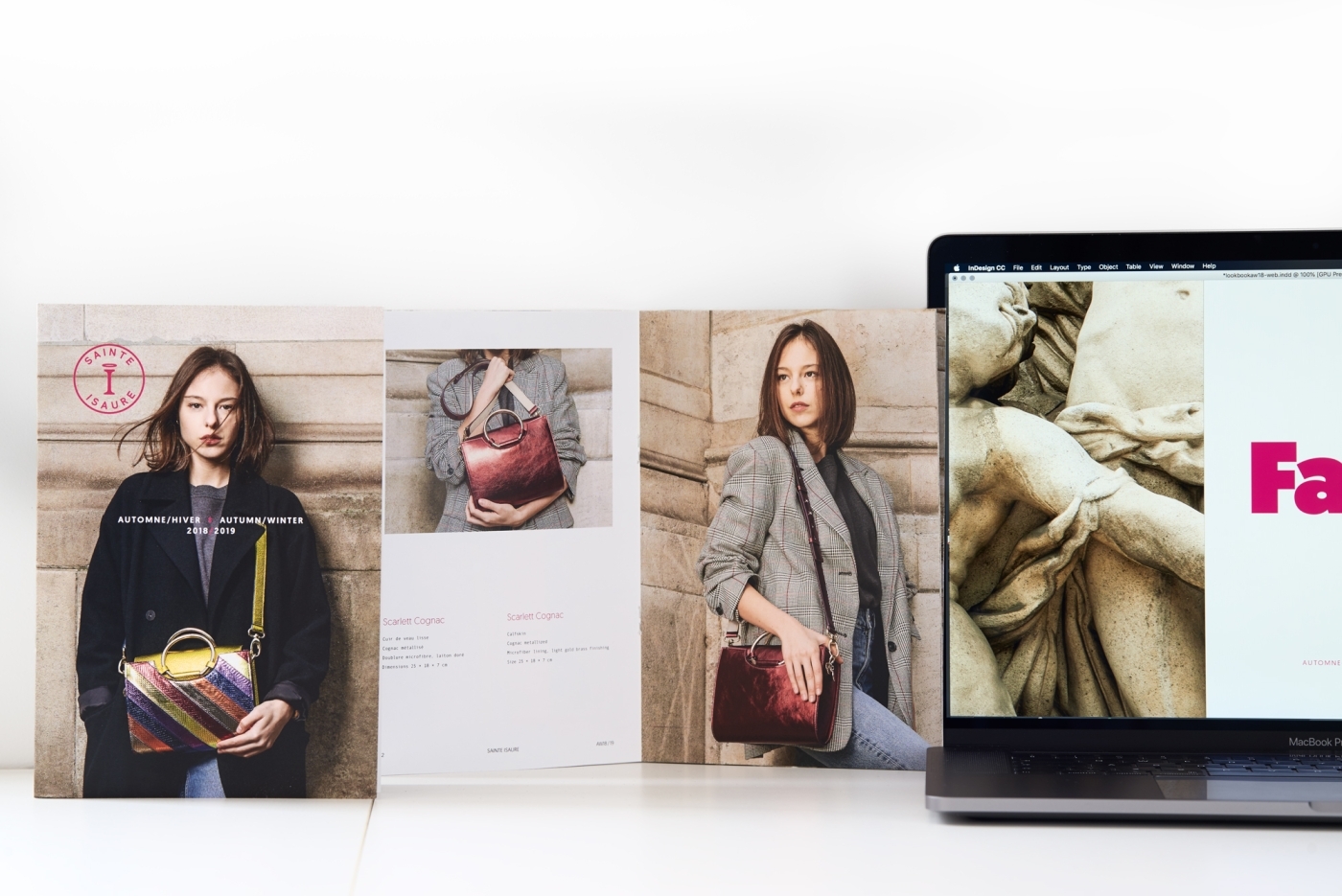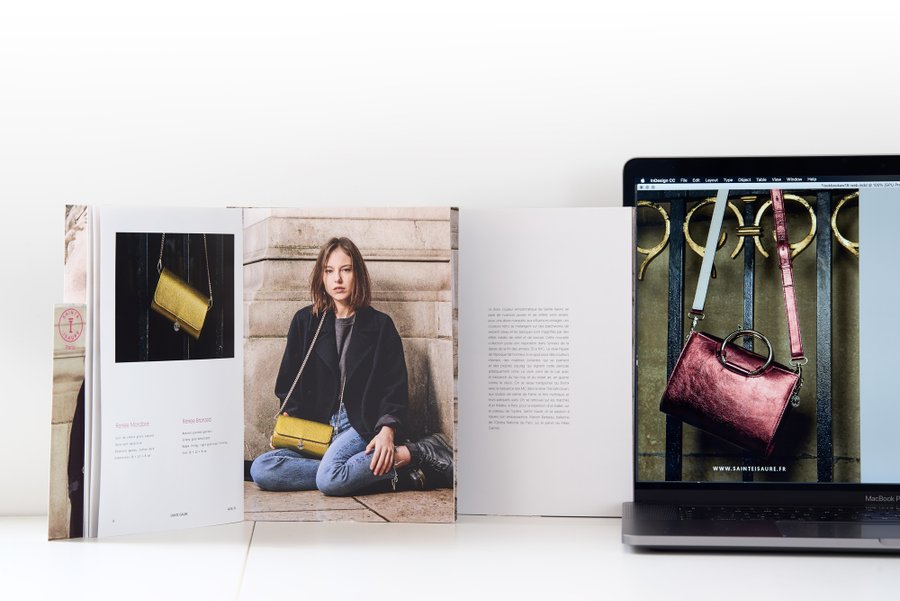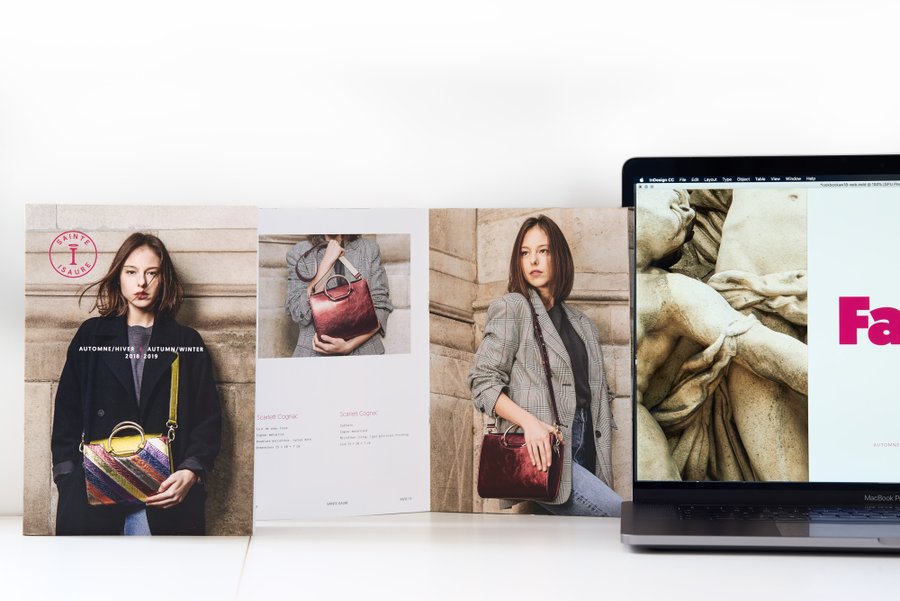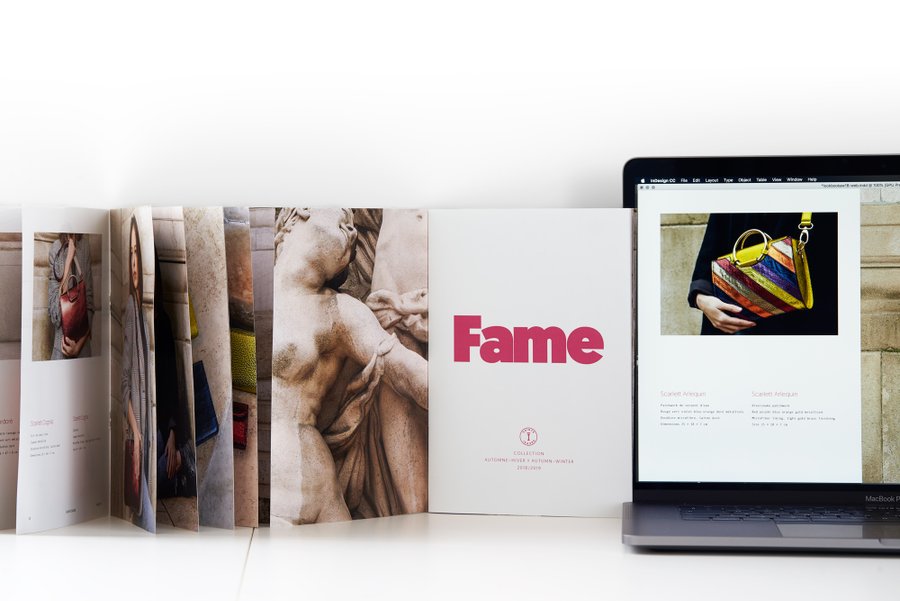
SainteIsaure lookbook AW 18
Conception graphique et mise en page du lookbook automne-hiver 2018 pour la marque de maroquinerie Sainte Isaure.
Inspirées par le thème de la danse, Sainte Isaure trouve le point d’équilibre entre un goût néoclassique et l’irrévérence juvénile.
Le parti pris graphique a été celui d’une mise en page sombre et sage qui met en valeur les photographies, tout en ajoutant l’impertinent rose fuchsia dans les textes.